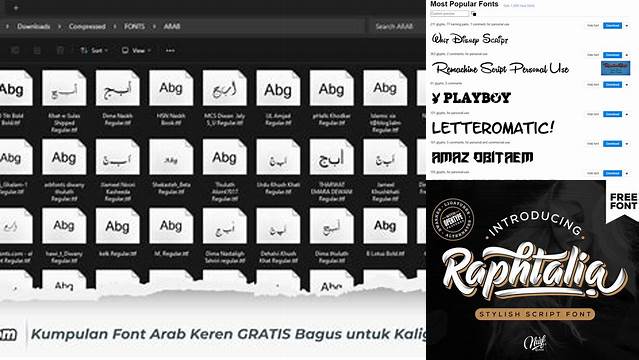
1. Mengapa Font Kaligrafi Keren Begitu Populer?
Font kaligrafi keren, guys, memang lagi naik daun banget! Kenapa ya? Nah, salah satu alasannya adalah karena font-font ini memberikan sentuhan elegan dan artistik pada desain apa pun. Bayangin aja, undangan pernikahan, logo, poster, atau bahkan konten media sosialmu bisa langsung terlihat lebih mewah dan menarik dengan sentuhan kaligrafi. Font kaligrafi bukan cuma sekadar tulisan, tapi juga sebuah karya seni yang bisa menghidupkan visual.
Selain itu, daya tarik font kaligrafi keren juga terletak pada fleksibilitasnya. Ada banyak banget jenis font kaligrafi yang bisa kamu pilih, mulai dari yang klasik dan formal sampai yang modern dan playful. Jadi, kamu bisa menyesuaikan font dengan tema dan gaya desain yang kamu inginkan. Misalnya, untuk desain yang elegan, kamu bisa pilih font kaligrafi dengan garis-garis yang halus dan anggun. Sementara itu, untuk desain yang lebih santai dan kreatif, kamu bisa coba font kaligrafi dengan sentuhan kuas yang dinamis.
Nggak cuma itu, font kaligrafi keren juga sering digunakan untuk memberikan kesan personal dan unik pada sebuah desain. Dengan memilih font yang tepat, kamu bisa menyampaikan pesan dengan lebih berkesan dan membuat desainmu lebih mudah diingat. Jadi, nggak heran kalau banyak desainer grafis, content creator, dan bahkan pemilik bisnis yang suka banget menggunakan font kaligrafi keren untuk mempercantik karya-karya mereka. Dengan berbagai pilihan gaya dan karakteristik, font kaligrafi keren menawarkan fleksibilitas tanpa batas untuk meningkatkan estetika visual dari berbagai proyek desain. Kalian semua pasti setuju kan?
2. Jenis-Jenis Font Kaligrafi Keren yang Wajib Kamu Tahu
Kalau kita ngomongin font kaligrafi keren, ada banyak banget jenisnya yang bisa bikin kamu bingung mau pilih yang mana. Tapi tenang, guys, gue bakal kasih beberapa rekomendasi jenis font kaligrafi yang wajib kamu tahu:
- Font Kaligrafi Klasik: Jenis font ini biasanya terinspirasi dari tulisan tangan para ahli kaligrafi zaman dulu. Ciri khasnya adalah garis-garis yang elegan, detail yang rumit, dan kesan yang formal. Contohnya adalah font seperti Brush Script MT, Edwardian Script ITC, dan Bickham Script Pro.
- Font Kaligrafi Modern: Nah, kalau yang ini lebih kekinian, guys. Font kaligrafi modern biasanya punya desain yang lebih simpel, bersih, dan mudah dibaca. Cocok banget buat desain-desain yang minimalis dan modern. Contohnya adalah font seperti Signatta, Hello Script, dan Stay Classy.
- Font Kaligrafi Bold: Buat kamu yang suka desain yang kuat dan tegas, font kaligrafi bold bisa jadi pilihan yang tepat. Font ini punya garis-garis yang tebal dan mencolok, sehingga cocok untuk judul, headline, atau logo. Contohnya adalah font seperti Black Jack, Streetwear, dan Bebas Neue.
- Font Kaligrafi Vintage: Kalau kamu pengen desain yang bernuansa retro dan klasik, font kaligrafi vintage bisa jadi solusinya. Font ini biasanya punya desain yang unik, dengan sentuhan tekstur dan ornamen yang khas. Contohnya adalah font seperti Lobster, Pacifico, dan Amatic SC.
Dengan memahami berbagai jenis font kaligrafi ini, kamu bisa lebih mudah memilih font yang sesuai dengan kebutuhan dan gaya desainmu. Jangan ragu untuk bereksperimen dan mencoba berbagai kombinasi font untuk menciptakan desain yang unik dan menarik!
3. Tips Memilih Font Kaligrafi Keren yang Sesuai dengan Kebutuhan
Memilih font kaligrafi keren itu nggak bisa sembarangan, guys. Ada beberapa hal yang perlu kamu perhatikan supaya font yang kamu pilih benar-benar sesuai dengan kebutuhan dan tujuan desainmu. Berikut ini beberapa tips yang bisa kamu ikuti:
- Tentukan Tema dan Gaya Desain: Sebelum memilih font, tentukan dulu tema dan gaya desain yang ingin kamu buat. Apakah desainmu bernuansa elegan, modern, vintage, atau playful? Dengan menentukan tema dan gaya desain, kamu bisa lebih mudah memilih font kaligrafi yang sesuai.
- Perhatikan Keterbacaan: Meskipun font kaligrafi keren itu penting, keterbacaan juga nggak boleh diabaikan. Pastikan font yang kamu pilih mudah dibaca, terutama jika digunakan untuk teks yang panjang. Hindari font dengan desain yang terlalu rumit atau garis-garis yang terlalu tipis.
- Sesuaikan dengan Media: Pertimbangkan media tempat desainmu akan ditampilkan. Jika desainmu akan dicetak, pastikan font yang kamu pilih terlihat jelas dan tajam saat dicetak. Jika desainmu akan ditampilkan di layar, pastikan font yang kamu pilih responsif dan terlihat bagus di berbagai ukuran layar.
- Coba Berbagai Pilihan: Jangan terpaku pada satu font saja. Coba berbagai pilihan font kaligrafi dan lihat mana yang paling cocok dengan desainmu. Kamu juga bisa mencoba mengkombinasikan beberapa font untuk menciptakan desain yang lebih unik dan menarik.
Dengan mengikuti tips ini, kamu bisa memilih font kaligrafi keren yang benar-benar sesuai dengan kebutuhan dan tujuan desainmu. Ingat, font yang tepat bisa membuat desainmu terlihat lebih profesional dan menarik!